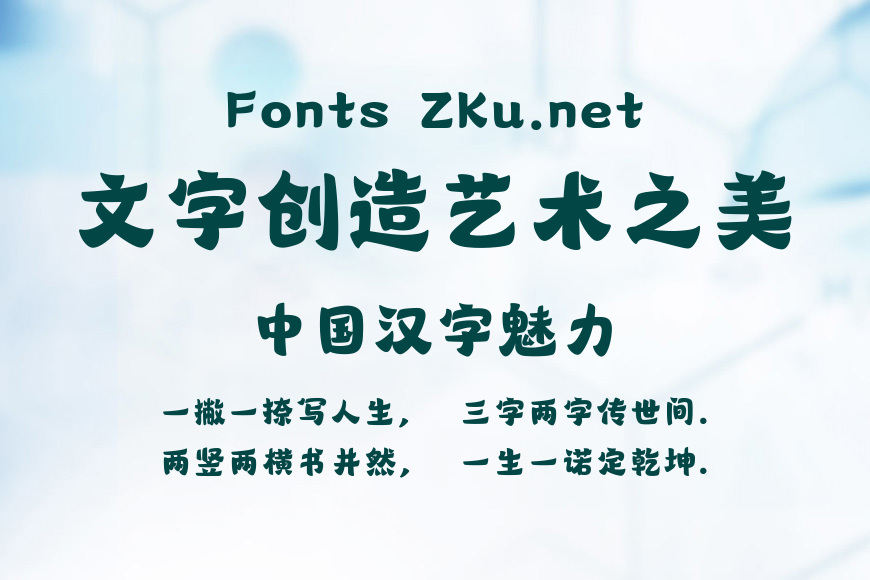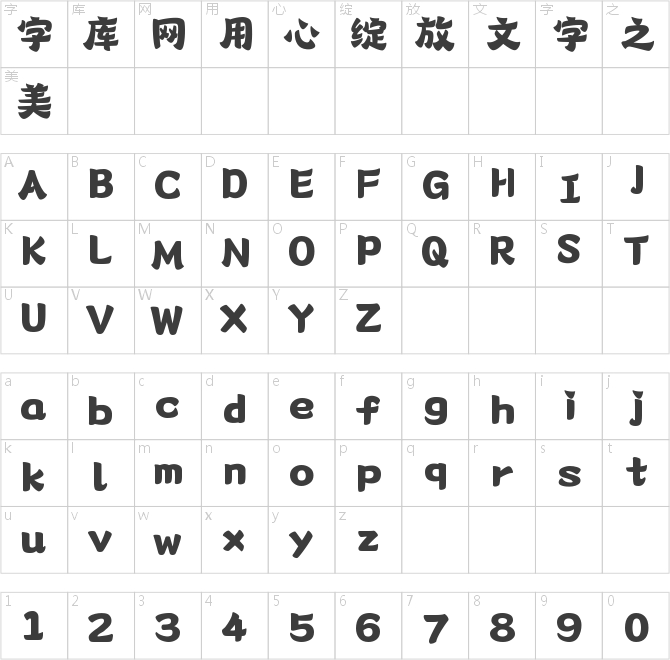
山海少年游
山海少年游介绍
山海少年游,一款卡通+国风风格的字体,包含简体汉字6763个。该字体字形童趣可爱,粗细对比明显,笔画笨拙微带曲线感。字体组合结构松散,多变灵动。同时又融入禅意书法的书写感,从而达到卡通童趣和国风书法的完美融合,从而使字体造型生动有趣,具有灵活的适用性,天真俏皮又具有国风书法感。